Eclipse Font 설정하기
== 8/11/2025 D2Coding 폰트 12폰트 예 ==
네이버에서 만든 개발자 폰트의 D2 Coding 폰트
개인적으로 최근까지 Eclipse를 사용할 때, 사용하는 폰트입니다.
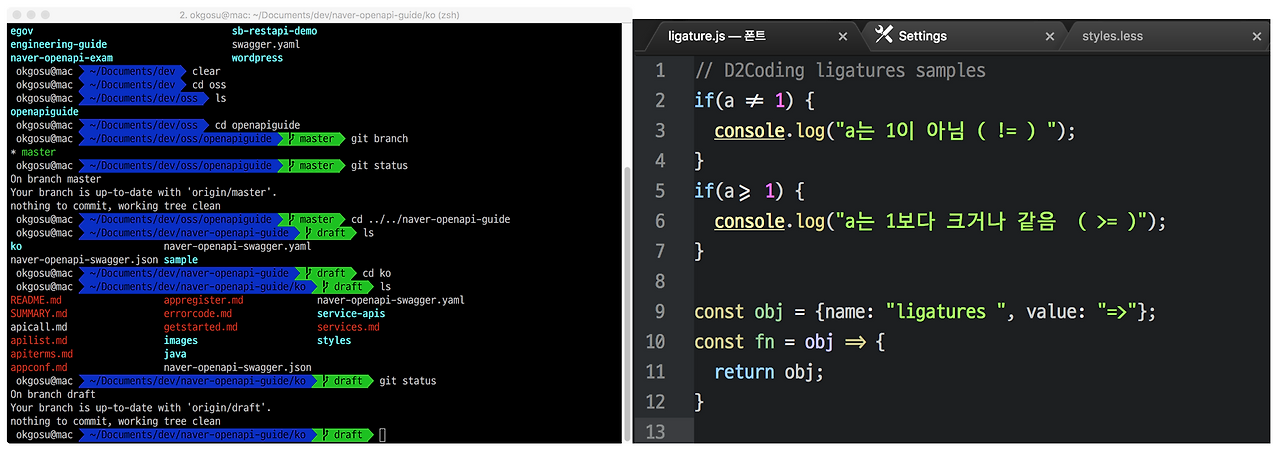
D2Coding 폰트의 사이즈는 12폰트로 해야 볼만한 사이즈로 나오더라구요.
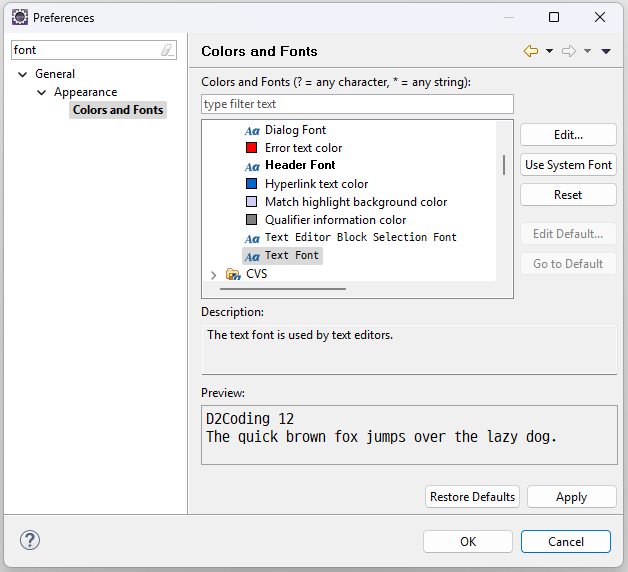
윈도우 환경에서 개발용으로 사용하는 폰트로 D2Coding 폰트를 사용하는 편입니다.
추가로
MAC OS에서 사용하는 Textmate의 기본 폰트인
Monaco Font :
- mac에서는 서체목록:Monaco, 글자체:일반체, 크기:11 를 놓고 쓴다.
- 윈도우에서는 11은 너무 크고, 10이 정당한것 같다. 9는 너무 작은 느낌이 든다.
Monaco 폰트는 개인적으로 너무 좋아하는 폰트중에 하나이다.
아쉽게도 window에서는 완벽하게 구현되는것 같지는 않아 아쉽긴하다.
그래도 아쉬운데로 괜찮은 편이다.
개인적으로 기본폰트 보다는 개발자 입장에서 가시성이 Monaco가 훨씬 괜찮죠.